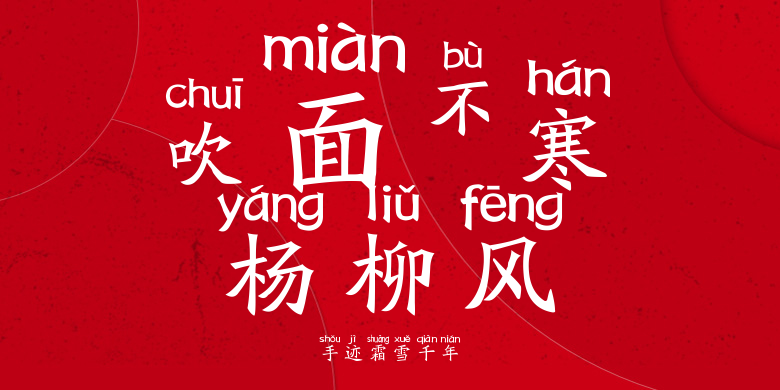
手迹霜雪千年
手迹霜雪千年,这款字体结构工整、笔画清晰,兼顾美观与易读性,适用于标题、正文、海报、包装、LOGO 等多种场景。字形优雅稳定,风格百搭耐看,适配日常排版与创意设计,让文字呈现更舒适、更具质感。手迹霜雪千年一笔一画,皆是细节,以均衡的比例、流畅的线条打造舒适视觉体验,字形端正大气,风格简约现代。无论是商业设计、品牌宣传还是日常排版,都能轻松驾驭,让文字更有格调与力量。手迹霜雪千年字体下载。